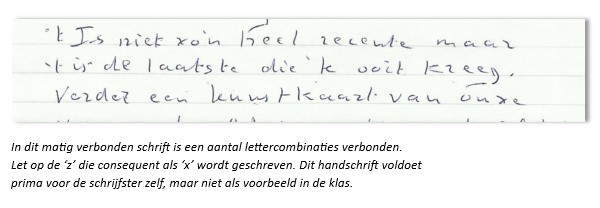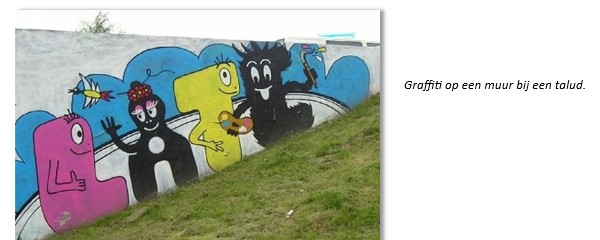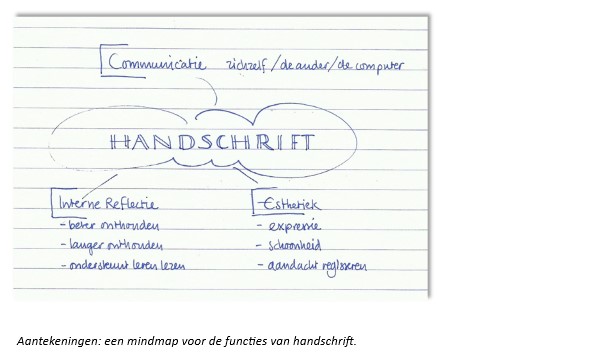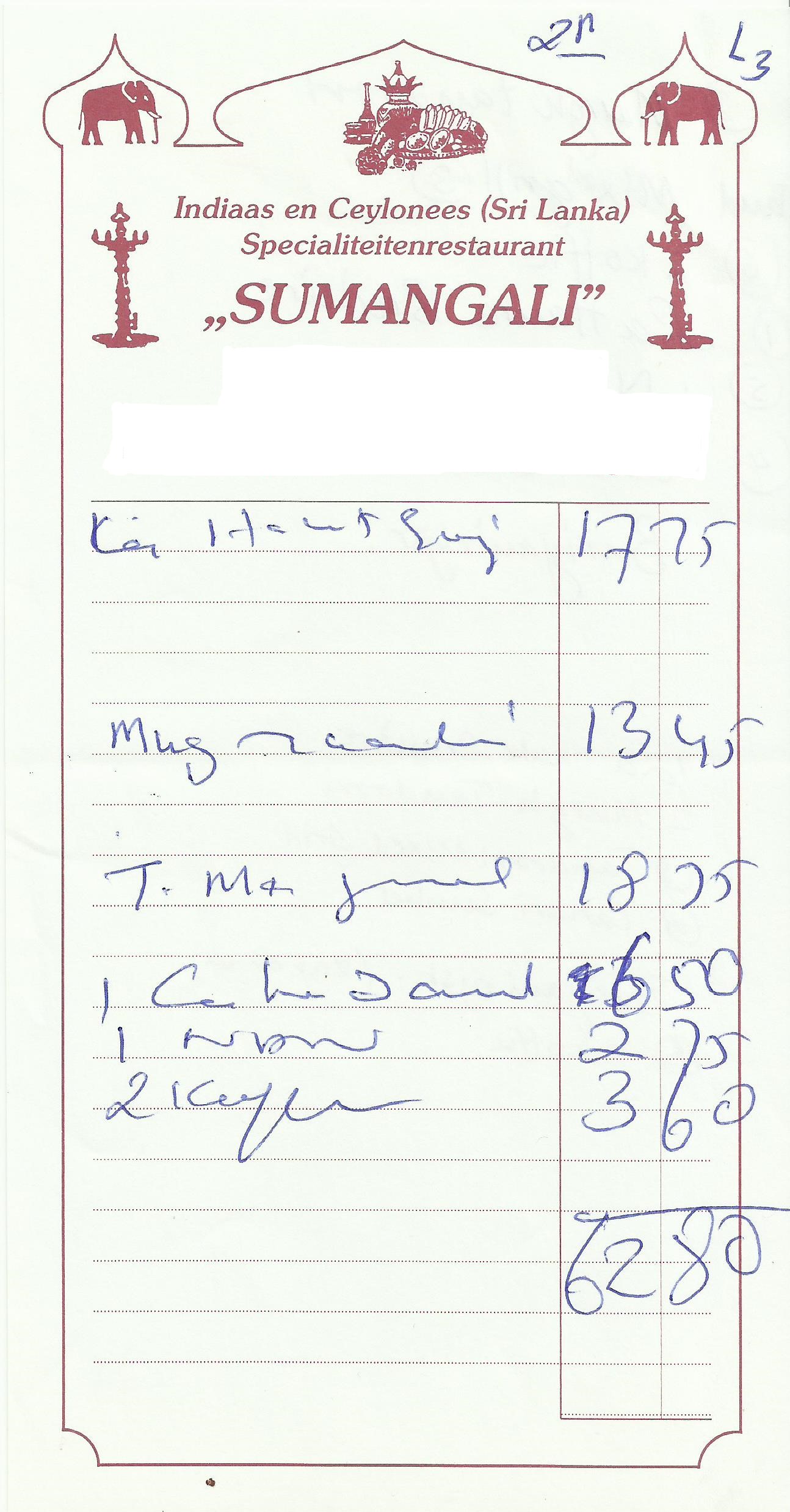
Wat komt in dit hoofdstuk aan bod?
In dit hoofdstuk staan de beschrijving, de achtergrondinformatie en de theorie bij hoofdstuk 2: ‘Wat is schrijven’ centraal. De student heeft deze informatie nodig om de opdrachten uit het werkschrift te kunnen maken. Naast de beschrijving ‘Wat is schrijven?’ komen aan de orde:
• Hoe schrijven wij?
1. Domein handschrift
2. Domein typschrift
3. Domein letteren
• De relatie tussen schrift en schrijven
· Intern reflectieve functie
· Communicatieve functie
· Transfer
Wat is schrijven?
Schrijven is het produceren van tekst en omvat zowel het stellen waarbij leerlingen leren naar inhoud en vorm teksten te produceren met verschillende communicatieve doelen, als de daarvoor benodigde schrifthandeling (Curriculum.nu, 2019).
Schrijven in de betekenis van stellen richt zich op de tekstinhoud: Waar wil ik overschrijven? Hoe verwoord ik een bepaalde gedachte? Hoe bouw ik mijn verslag op? Hoe verleid ik de lezer om door te lezen?
De schrifthandeling voor handschrift, typschrift en letteren die je daarvoor nodig hebt, richt zich op de visuele vorm: hoe produceer ik een gelijkmatig en duidelijk leesbaar schrift? Hoe visualiseer ik de structuur van de tekst? Hoe geef ik koppen, opsommingen en aanvullende teksten vorm? Hoe kan ik de inhoud ondersteunen en hoe leid ik hem door de tekst?
Van Schrift Naar Schrijven richt zich op het aanleren van de schrifthandeling in relatie tot de persoon en de taak die hij moet uitvoeren.
Hoe schrijven wij?
Schrift kun je langs twee motorische systemen produceren:
• M.b.v. orale aansturing: mondeling door spraakherkenning. De computer herkent klanken en zet die met behulp van software om in geschreven tekst.
• M.b.v. manuele aansturing: met de hand. Dat doe je:
• met handschrift: door letters te vormen met bijvoorbeeld een pen;
• met typschrift: door toetsen in te drukken of aan te tippen.
Werk je met spraakherkenning, dan moet je goed (laten) articuleren en heb je accurate en goed werkende software nodig.
Spraakherkenning kan handig zijn in situaties waarin je alleen bent, bijvoorbeeld als je de computer in je auto of apparaten in je huis via stemcommando’s wilt bedienen. Je kunt ook een tekst dicteren.
Spraakherkenning is een vorm van ‘hardop’ werken die ongeschikt is in sociale ruimtes als een treincoupé, een gedeelde werkkamer, een flexplek, een bibliotheek, studiezaal of klaslokaal. Daarom richt handschriftonderwijs zich (voorlopig nog alleen) op de manuele vaardigheden handschrift en typschrift (10voordeleraar, 2018).
Wat je ook met de hand schrijft, je kunt kiezen uit drie essentieel verschillende manieren, namelijk de domeinen:
1. Handschrift.
2. Typschrift.
3. Letteren.
Wil je jouw leerlingen kunnen begeleiden, dan is kennis en kunde m.b.t. de drie domeinen een voorwaarde.
1. Domein handschrift
Je handschrift is het alledaagse schrift dat je gebruikt als je bijvoorbeeld aantekeningen noteert, een mindmap maakt of een to-do lijstje of boodschappenbriefje voor jezelf schrijft.
2. Domein typschrift
Typschrift gebruik je bij digitale communicatie (je stuurt een appje), als je een powerpoint maakt en een verslag of rapport opstelt.
3. Domein letteren
Letteren doe je voor je plezier of als je de aandacht op iets wilt vestigen, bijvoorbeeld op aanbiedingen in winkels, op de specialiteit van de dag in de horeca, op slogans of op spandoeken.
De relatie tussen schrift en schrijven
Schrijven draagt bij aan taalontwikkeling en meer specifiek aan de geletterdheid van kinderen. Voor eind groep 8 streeft het basisonderwijs naar functionele geletterdheid: voldoende kunnen lezen en schrijven om te kunnen functioneren in de maatschappelijke context. Denk bijvoorbeeld aan het begrijpen van een gebruiksaanwijzing bij een nieuw apparaat of een bijsluiter bij medicijnen. Maar ook aan het lezen van de ondertiteling op tv of het plannen van een reis, het invullen van een enquête of het gebruiken van je agenda.
Niet alle volwassenen bereiken dit niveau. In Nederland zijn anno 2019 ongeveer 2.5 miljoen(!) mensen laaggeletterd, wat wil zeggen dat ze onvoldoende kunnen lezen en schrijven om dat in hun dagelijks leven te gebruiken (Stichting Lezen & Schrijven). Sommige mensen zijn analfabeet en kunnen in het geheel niet lezen of schrijven. In Nederland zijn naar schatting 250.000 mensen analfabeet. Kortom: werk aan de winkel!
Schrijven is een complexe vaardigheid met taal- en schriftaspecten. Tijdens het schrijven wisselen plannen, schrijven en reviseren (herzien) elkaar voortdurend af en die drie aspecten beïnvloeden elkaar sterk, zowel m.b.t. de talige kant van het schrijfproces als tijdens de schrifthandeling.